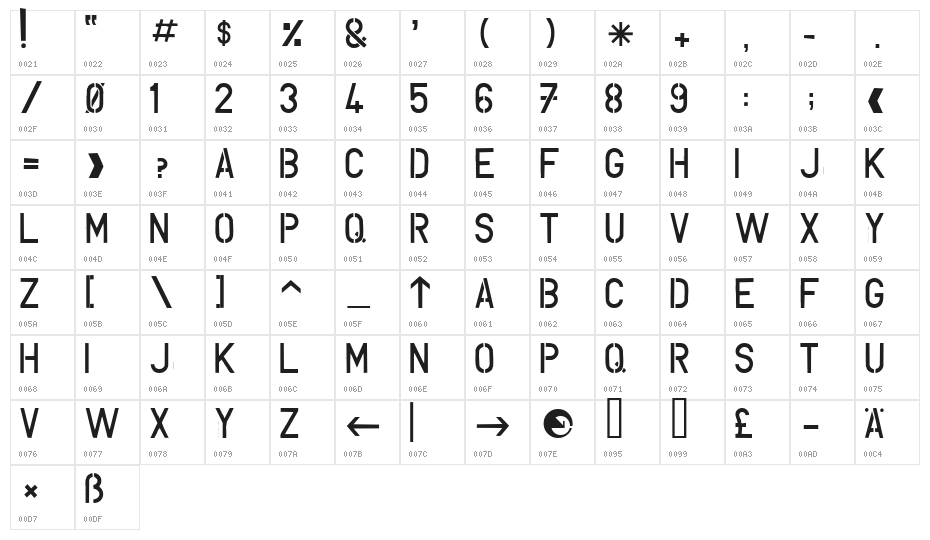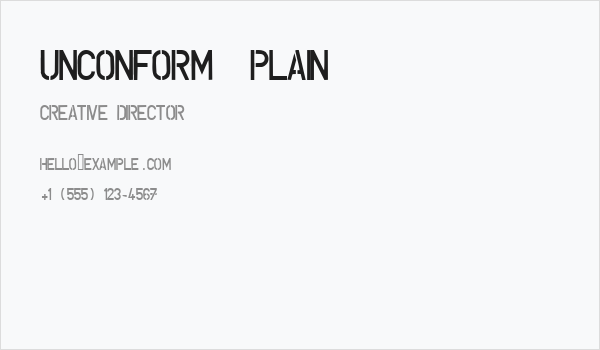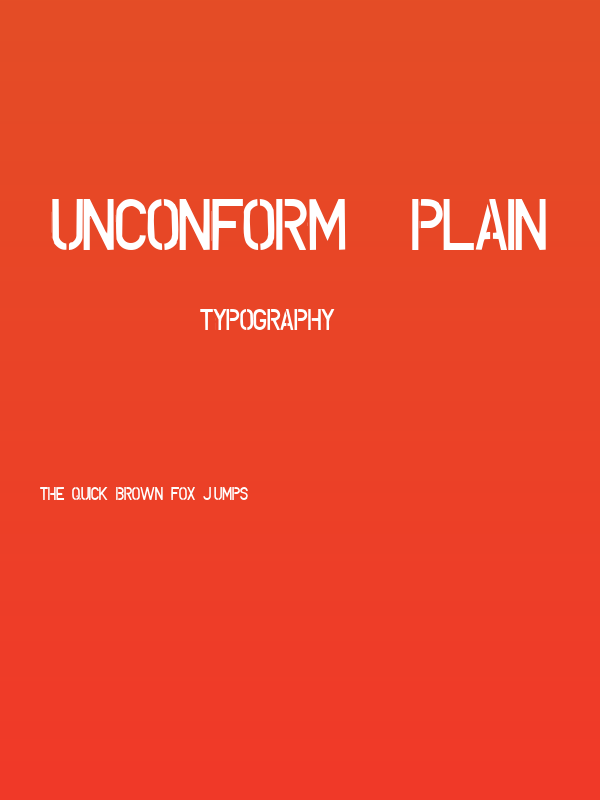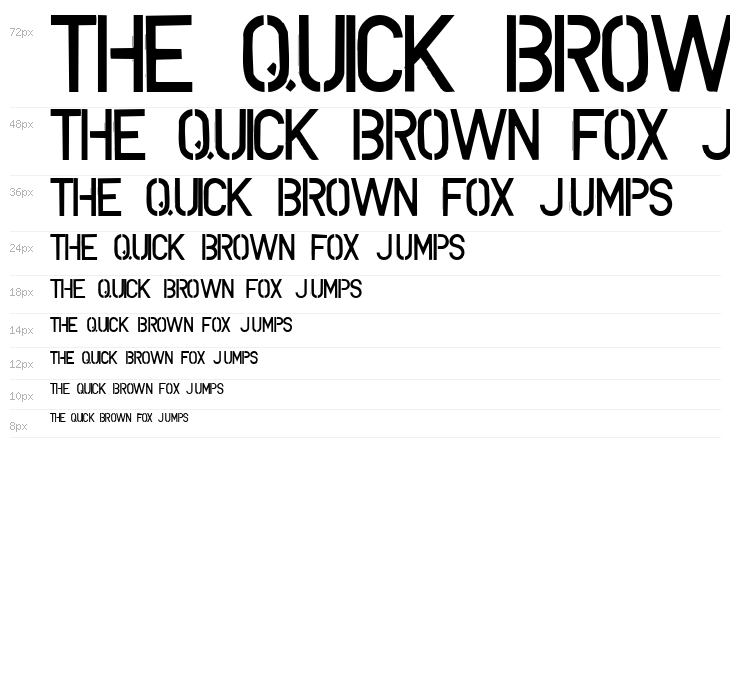
UNCONFORM plain Font
Brian McFeely
| Vorgeschlagene Projekte | Ideal for branding, headlines, posters, and digital media where a strong, modern presence is desired. |